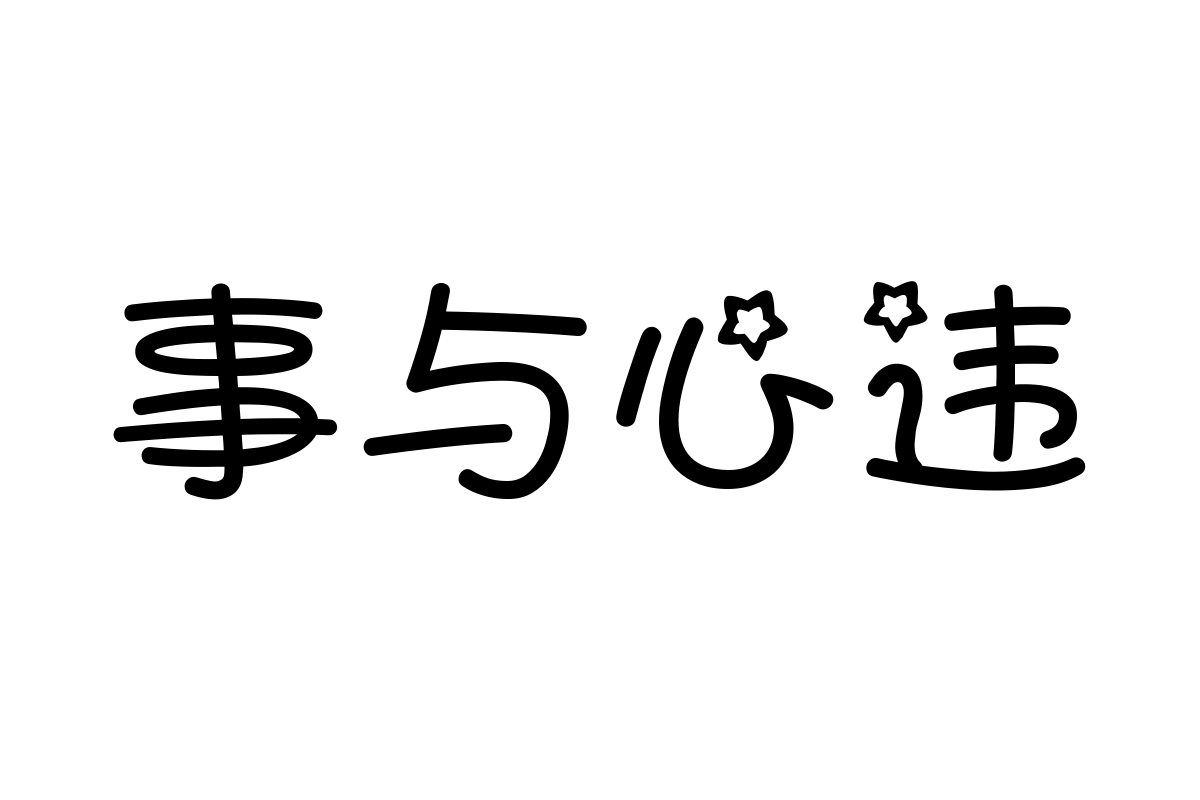
字体管家水瓶座是一款由字体管家推出的免费中文字体,具有独特的艺术风格和设计感。这款字体适用于各种设计场景,如海报、宣传册、名片等。
字体管家水瓶座的特点如下:
1. 简洁大方:字体线条流畅,整体结构紧凑,给人一种简约大气的感觉。
2. 独特性:字体采用了抽象的水瓶座元素,使整个字体更加具有个性和创意。
3. 易读性:字体的线条粗细适中,使得文字在阅读时更加舒适。
4. 适应性强:这款字体适用于多种场景,无论是正式场合还是休闲场合,都能展现出其独特的魅力。